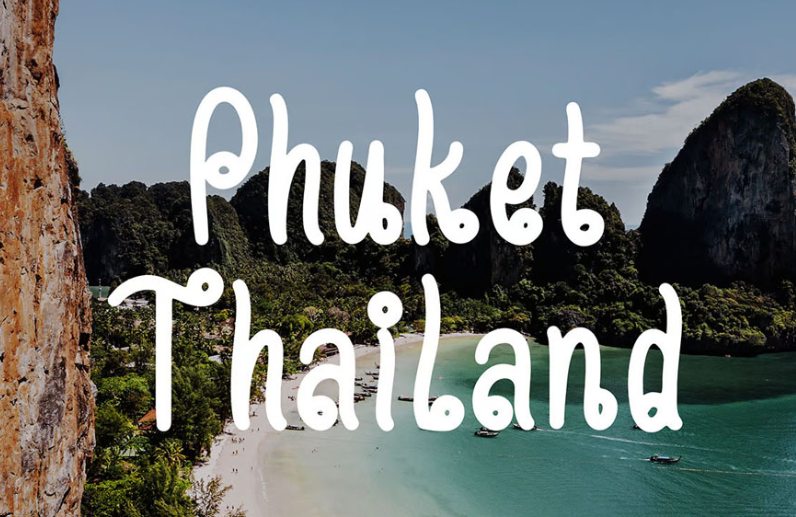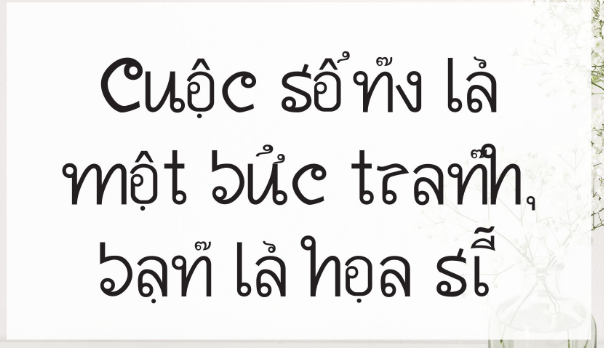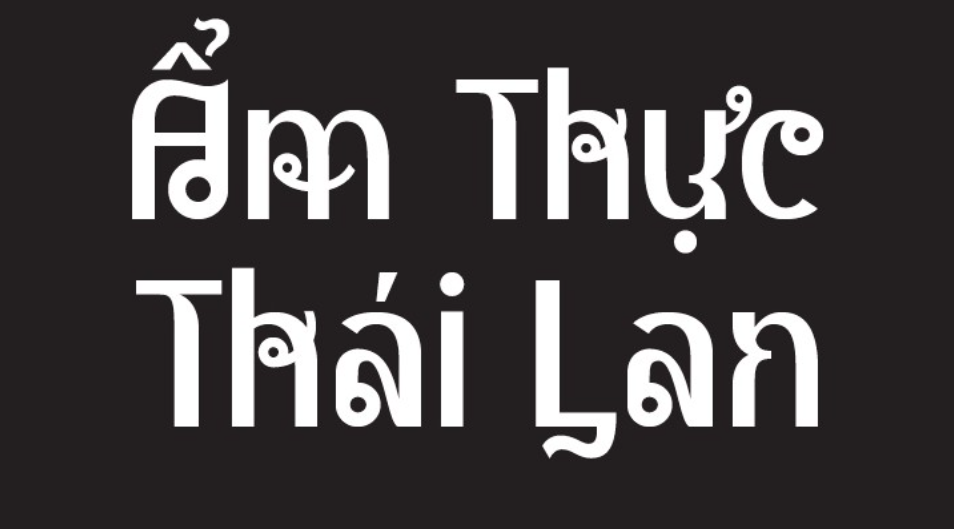
Font chữ Thái – Tổng hợp font chữ Thái Lan đẹp, độc đáo và ấn tượng
Font chữ Thái là nguồn tài nguyên đồ họa quan trọng dành cho các nhà thiết kế khi thực hiện các dự án bao bì hàng xuất nhập khẩu sang thị trường Đông Nam Á, hoặc thiết kế bộ nhận diện cho các chuỗi ẩm thực xứ chùa Vàng. Trong thiết kế hiện đại, nhóm phông chữ này bao gồm cả hệ chữ tiếng Thái bản địa chuẩn Unicode và các dòng Font chữ kiểu Thái Lan được Việt hóa khéo léo để gõ chữ Quốc ngữ nhưng mang đậm nét thẩm mỹ đặc trưng của Thái Lan. Doozypack.vn chia sẻ link download Font chữ Thái Lan trọn bộ chuẩn kỹ thuật, giúp bạn sở hữu kho phông chữ phong phú mà không lo gặp lỗi hiển thị dấu thanh khi thiết kế in ấn.
Phân loại các nhóm font chữ Thái Lan phổ biến nhất
Trước khi bắt đầu tải font, bạn cần xác định rõ mục đích sử dụng để chọn đúng nhóm phông chữ phù hợp với yêu cầu thực tế của sản phẩm.
Mẫu chữ Thái truyền thống
Font chữ tiếng Thái bản địa chuẩn Unicode
Đây là nhóm Font chữ tiếng Thái Lan thực thụ phục vụ cho việc soạn thảo ngôn ngữ Thái. Hệ thống này được chia thành hai nhánh chính: dòng chữ truyền thống có các vòng tròn nhỏ ở đầu nét (looped) mang vẻ đẹp cổ điển và dòng Font chữ Thái hiện đại lược bỏ vòng tròn (loopless) mang phong cách tối giản, tương tự như phông chữ không chân Helvetica phương Tây. Các bộ Font chữ tiếng Thái thông dụng như Sukhumvit, Prompt hay Kanit là lựa chọn bắt buộc cho các thông tin pháp lý, bảng thành phần dinh dưỡng và hướng dẫn sử dụng trên bao bì hàng xuất khẩu.
Font chữ Thái Việt hóa mô phỏng độc đáo
Nếu bạn đang tìm kiếm Font chữ Thái Lan đẹp để làm logo hoặc tiêu đề cho quán ăn Thái, trà sữa Thái hay các món ăn vặt Tom Yum, nhóm Font chữ Thái Việt hóa là giải pháp hoàn hảo. Đây là các ký tự chữ cái tiếng Việt nhưng các đường nét được uốn lượn, cách điệu mô phỏng theo cấu trúc chữ cái của Thái Lan, mang lại cảm giác bản địa sống động ngay từ cái nhìn đầu tiên.
Ưu điểm khi sử dụng font chữ tiếng Thái thông dụng chuẩn kỹ thuật
Khi ứng dụng các phông chữ ngôn ngữ đặc thù vào sản xuất bao bì tại Doozypack.vn, sự chuẩn xác về mặt kỹ thuật mang lại nhiều giá trị thiết thực:
• Tuân thủ quy chuẩn bao bì xuất khẩu: Một mẫu bao bì xuất khẩu sang Thái Lan nếu bị lỗi hiển thị ký tự phụ hoặc dấu thanh điệu sẽ bị từ chối thông quan. Sử dụng Font tiếng Thái chuẩn Unicode giúp bạn an tâm tuyệt đối về mặt pháp lý.
• Tối ưu hóa khả năng đọc hiểu: Các dòng Font chữ Thái Lan hiện đại có cấu trúc thoáng đãng, giúp người tiêu dùng bản địa dễ dàng nắm bắt thông tin sản phẩm trên kệ hàng.
• Tạo dấu ấn nhận diện đậm nét: Các dòng phông chữ kiểu Thái giúp thương hiệu ẩm thực của bạn định vị rõ ràng bản sắc trong tâm trí khách hàng Việt Nam.
Kiểu chữ Thái độc đáo
Nhóm Font Đặc điểm thị giác Ứng dụng đề xuất tại Doozypack.vn
Thai Unicode Loopless Hiện đại, không chân, tối giản Bao bì xuất khẩu, thông số kỹ thuật, tem nhãn phụ.
Thai Traditional Looped Đầu tròn cổ điển, trang trọng Bao bì trà thảo mộc, nhãn dầu xoa bóp, dược phẩm.
Font kiểu Thái Việt hóa Gõ tiếng Việt phong cách Thái Logo nhà hàng Thái, hộp đồ ăn vặt, banner sự kiện.
Lời khuyên từ xưởng in: Đối với các bao bì xuất khẩu sang thị trường Thái Lan tại Doozypack.vn, bạn nên ưu tiên sử dụng Font chữ Thailand dạng OTF. Bản OTF giúp hệ thống dấu thanh điệu đa tầng của tiếng Thái hiển thị chuẩn xác ở đúng cao độ, không bị đè nét lên thân chữ khi xuất file PDF in Offset.
03 Ứng dụng thực tế của font chữ Thailand trong sản xuất bao bì
Sự độc đáo của phông chữ Thái Lan mang lại hiệu ứng thị giác đắt giá trên các dòng sản phẩm bao bì thực tế do Doozypack.vn sản xuất:
• Hộp giấy ẩm thực Thái & Đồ ăn nhanh: Tiêu đề thương hiệu in bằng font kiểu Thái trên hộp xôi xoài, hộp pad thai hay túi giấy đựng gà rán tạo nên vẻ ngoài đậm đà phong vị bản xứ.
• Tem nhãn dán Mỹ phẩm & Trà sữa Thái Lan: Dùng cho các sản phẩm trà sữa Thái xanh, Thái đỏ hoặc mỹ phẩm xách tay, giúp khách hàng nhận diện nguồn gốc sản phẩm nhanh chóng.
• Bao bì nông sản xuất khẩu: In thông tin song ngữ Việt – Thái chuẩn mực trên hộp carton đựng thanh long, xoài sấy xuất khẩu sang thị trường láng giềng.
Thiết kế chữ mang nét Á Đông
03 Lưu ý kỹ thuật khi in ấn với phông chữ Thái Lan đa tầng thanh điệu
Việc sản xuất bao bì thực tế sử dụng tiếng Thái đòi hỏi sự am hiểu kỹ thuật chuyên sâu tại xưởng in Doozypack.vn:
• Kiểm soát khoảng cách dòng (Leading): Tiếng Thái có hệ thống dấu thanh và nguyên âm nằm ở 4 tầng cao độ khác nhau (trên đầu và dưới chân chữ cái). Designer cần nới rộng khoảng cách dòng chữ tối thiểu 1.5 lần so với chữ Latinh để các dấu không chạm vào dòng trên hoặc dòng dưới.
• Kiểm soát kích thước chữ tối thiểu: Các dấu thanh điệu tiếng Thái khá nhỏ. Khi in trên giấy Kraft thô nhám, bạn nên để size chữ tối thiểu từ 8pt trở lên để thớ giấy không làm mất các dấu thanh quan trọng này.
5. In chữ Thái trên hộp giấy màu tối bằng kỹ thuật gì đẹp nhất?
Doozypack.vn khuyên bạn nên sử dụng kỹ thuật ép kim nhũ vàng hoặc in lụa màu trắng. Sự tương phản sắc nét này sẽ làm nổi bật vẻ đẹp độc đáo của các nét uốn lượn chữ Thái trên nền hộp tối màu.